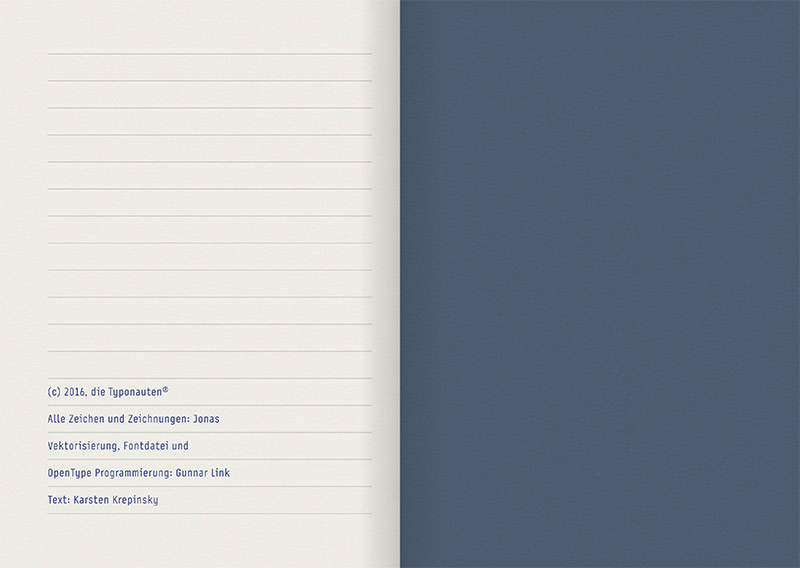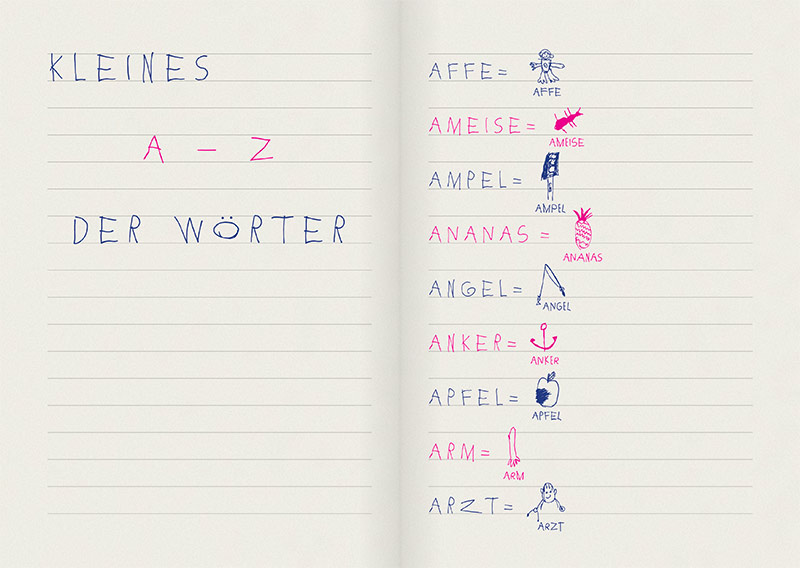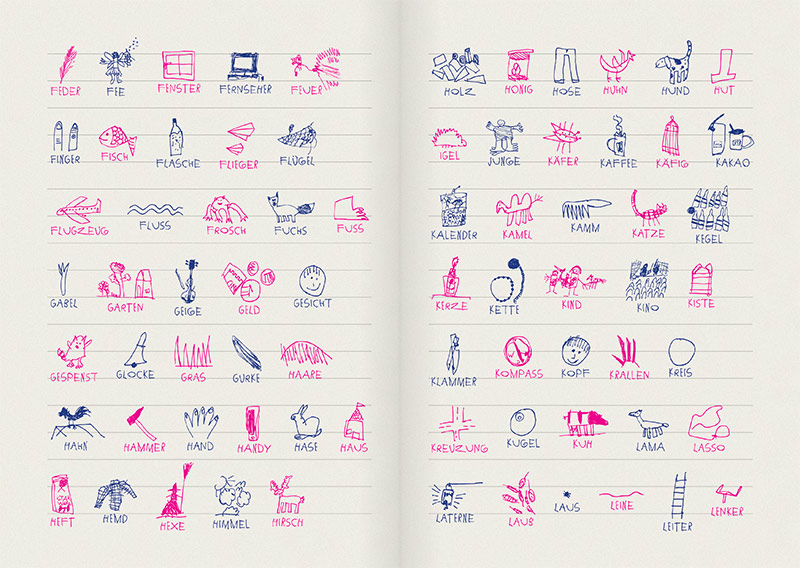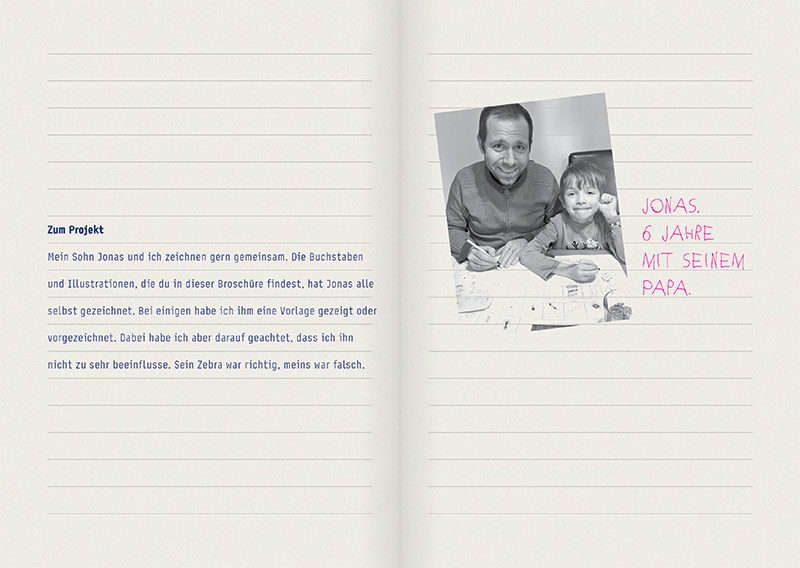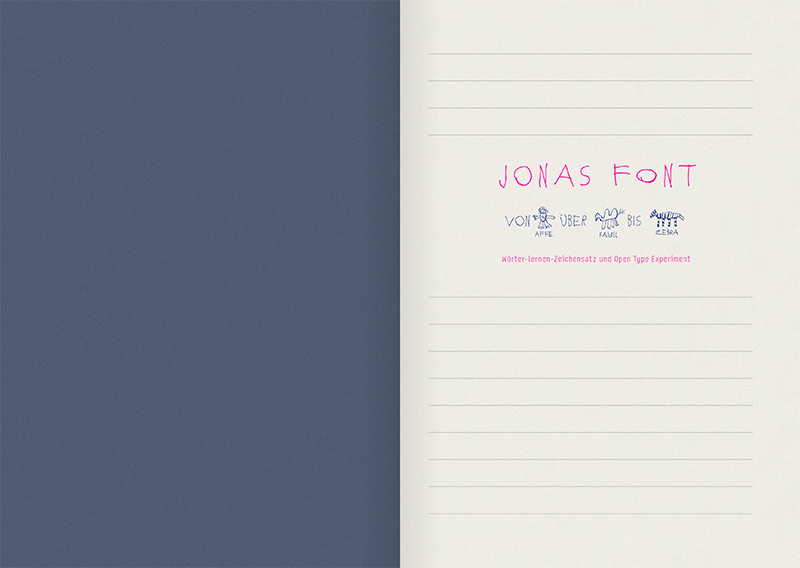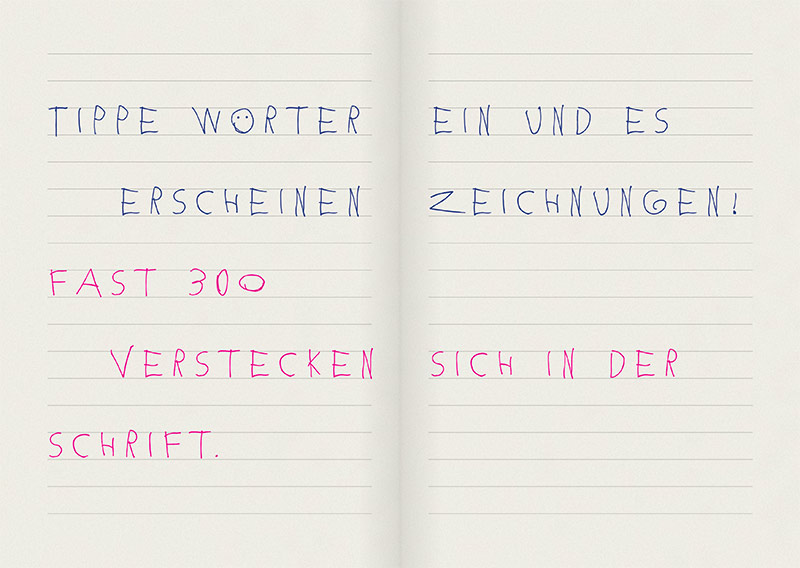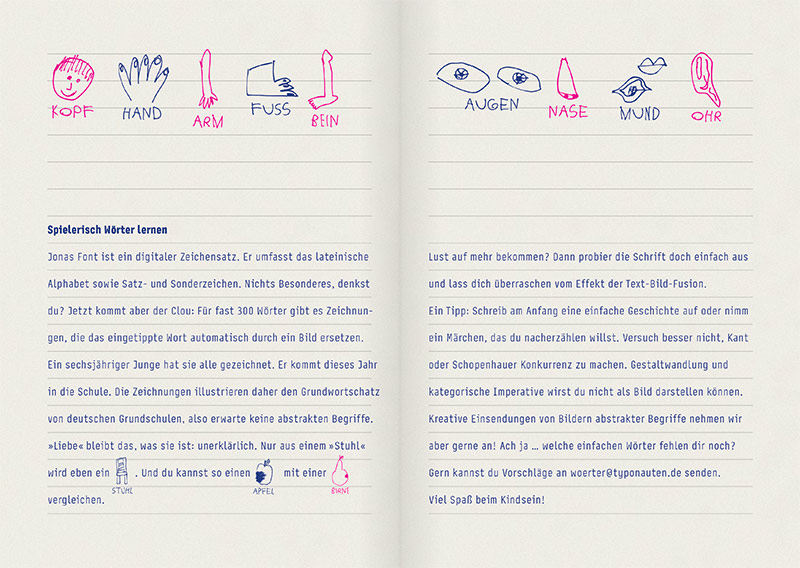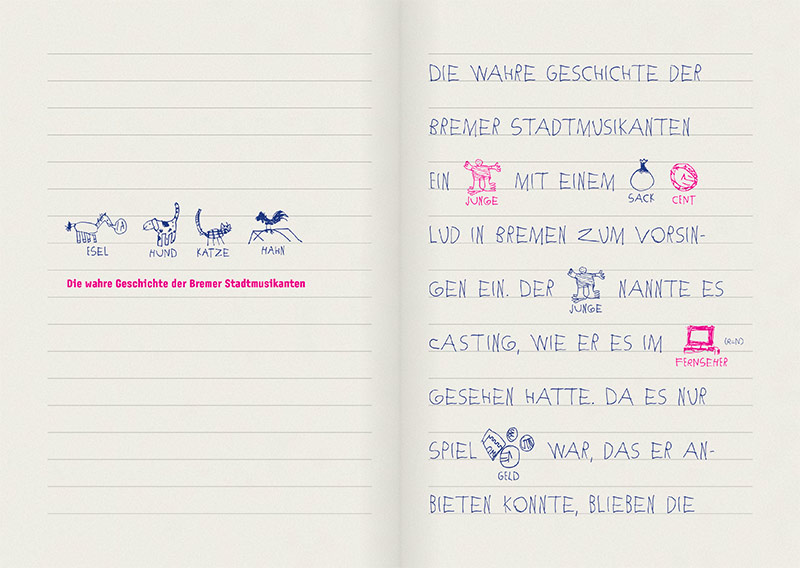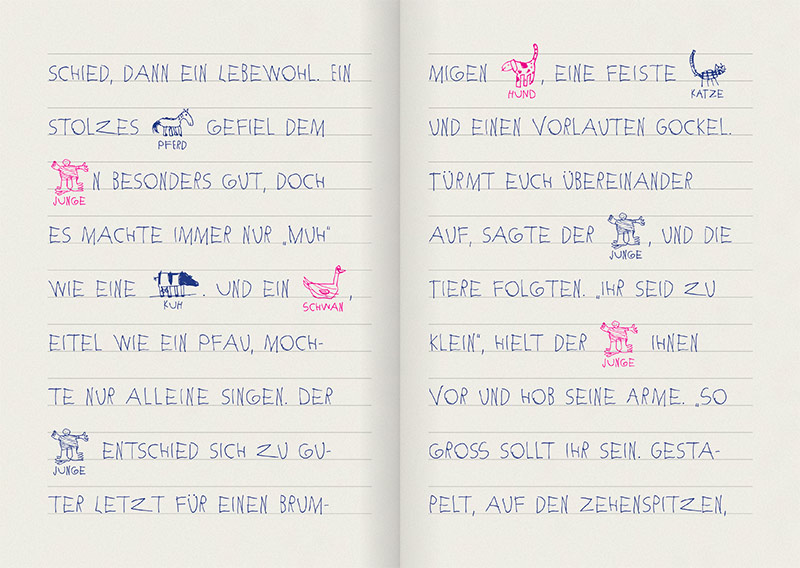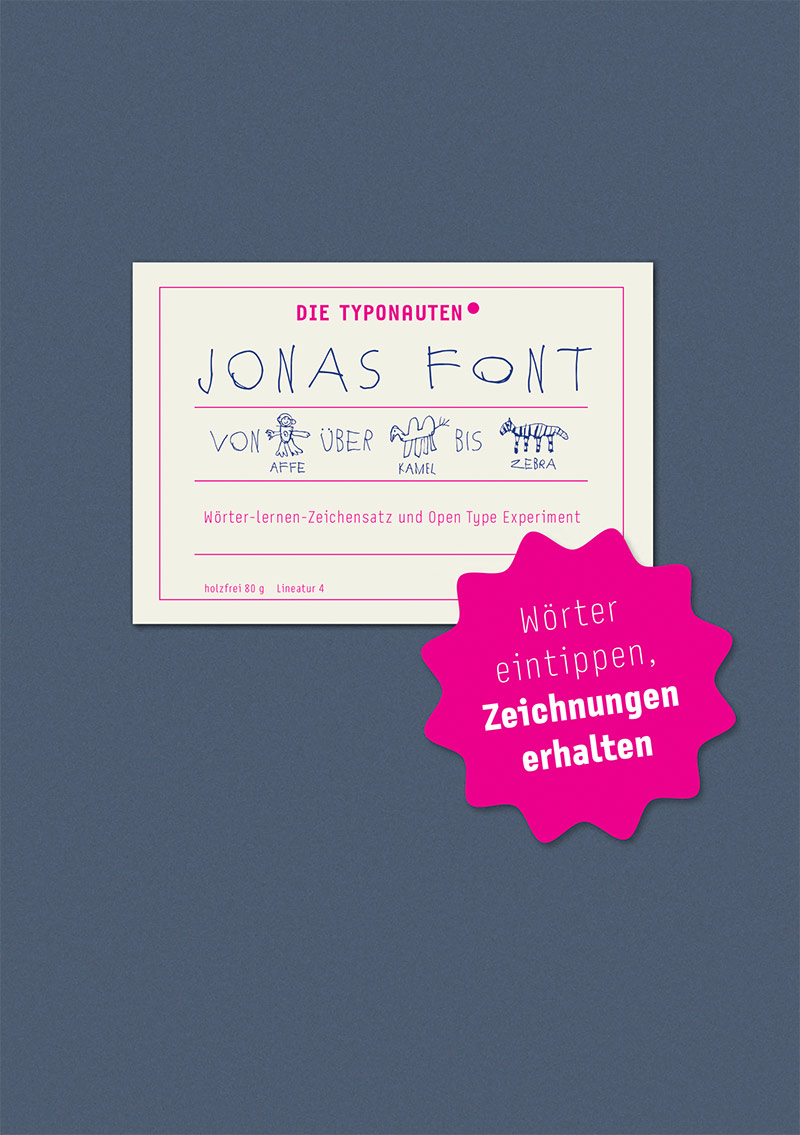
Spielerisch Wörter schreiben mit Jonas Font
Zum Schulanfang verschenkt die Designagentur die Typonauten die Schrift Jonas Font. Jonas Font ist ein digitaler Zeichensatz, der das lateinische Alphabet sowie Satz- und Sonderzeichen umfasst. Das ist nichts Besonderes, aber der Clou ist, dass es für fast 300 Wörter Zeichnungen gibt, die das eingetippte Wort automatisch durch ein Bild ersetzen. Diese Bilder hat ein sechsjähriger Junge, der dieses Jahr in die Schule gekommen ist, liebevoll gezeichnet. Die Zeichnungen illustrieren den Grundwortschatz deutscher Grundschulen. Gezeichnet wurden keine abstrakten Begriffe. »Liebe« bleibt das, was es ist: unerklärlich. Nur aus einem »Stuhl« wird eben eine Zeichnung vom Stuhl. Und so kann man einen Apfel mit einer Birne vergleichen. Die Schrift gibt es kostenlos zum Downloaden auf der Website www.typonauten.de/jonas
Open Type: Kontextbedingte Varianten
Dieser sperrige Fachbegriff ist der Schlüssel zu Jonas Font. Normalerweise sind damit Zeichenkombinationen gemeint, wie z.B. Ligaturen (fi, fl, ff ...). Dabei wird bei einer bestimmten Zeichenkombination eine optische Alternative eingesetzt. Statt einer solchen Zeichenkombination kann man aber auch eine Zeichnung hinterlegen. Das ist eine ganz neue Anwendungsidee und wurde so noch nie verwirklicht.
Zum Projekt
Die Buchstaben und Illustrationen hat ein sechsjähriger Junge gezeichnet. Bei einigen hat sein Vater geholfen, indem er ihm eine Vorlage gezeigt oder vorgezeichnet hat. Dabei hat der Vater darauf geachtet, dass er seinen Sohn möglichst wenig beeinflusst. Sein Zebra war richtig, das des Vaters war falsch.